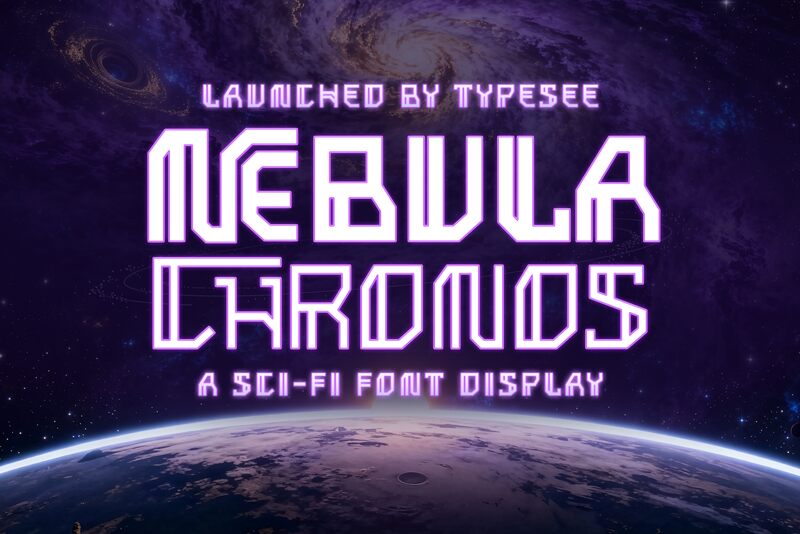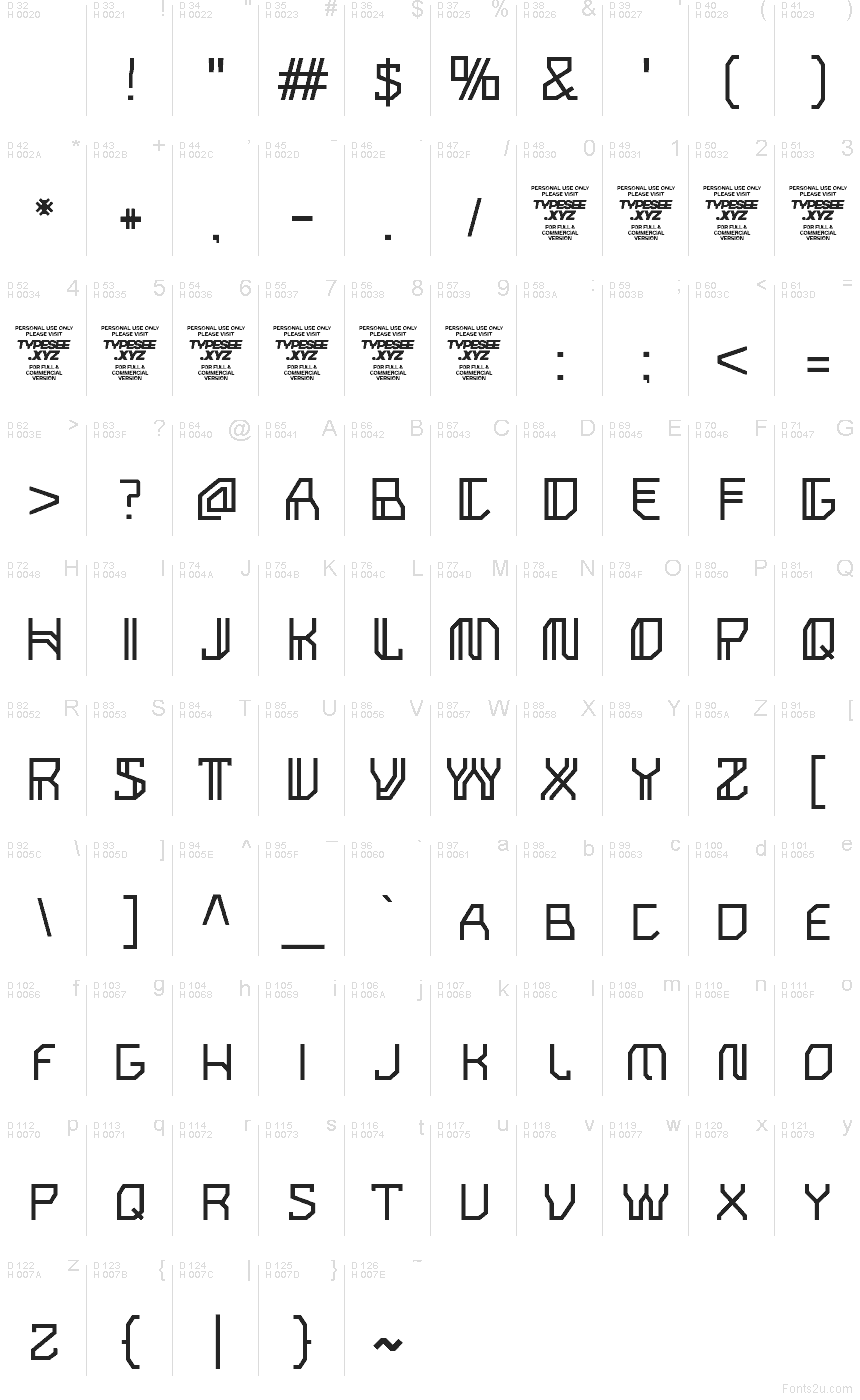
Nebula Chronos Regular от Typesee Type Foundry - это бесплатный футуристический шрифт для заголовков. Резкие угловатые срезы, квадратные изгибы и узкая, модульная структура придают буквам техничный, космический ритм. Повторяющиеся прямые грани и четкие соединения делают дизайн геометрически выверенным и организованным, сохраняя при этом выразительный научно-фантастический характер.
Nebula Chronos - это бесплатный шрифт, который отлично подходит для научно-фантастических плакатов, техно-брендинга, логотипов игр, титульных карточек, графики для мероприятий и акцентных текстов. Его граненый стиль также идеально смотрится на упаковках, в моушн-графике и цифровых заголовках, когда вам нужен шрифт, выглядящий спроектированным и намеренно стилизованным.